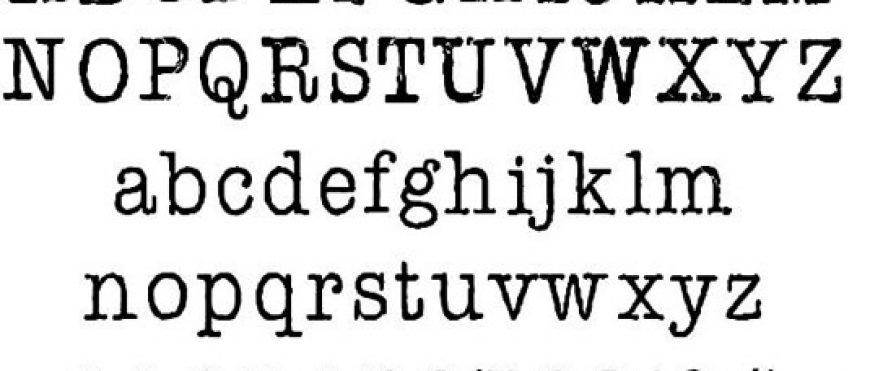
Создание атмосферы ретро: идеальный шрифт в стиле печатной машинки для ваших проектов
Шрифт в стиле печатной машинки приносит в дизайн ностальгическую атмосферу и ретро-шарм. Он идеально подходит для создания винтажных и креативных проектов, а также может быть использован для акцентов в современных дизайнах. В этой подборке вы найдете лучшие примеры таких шрифтов, а также полезные советы по их применению для достижения максимального эффекта.
При выборе шрифта в стиле печатной машинки обращайте внимание на его читаемость. Некоторые такие шрифты могут быть сложными для восприятия текста на экране.
Не бойтесь комбинировать шрифт в стиле машинки с современными элементами дизайна, чтобы создать интересный контраст между ретро и современностью.
Для улучшения визуального восприятия используйте шрифт в стиле печатной машинки в крупных заголовках, а не в длинных текстах, чтобы избежать перегрузки.
Если ваш проект связан с текстами, которые должны выглядеть как старые документы, выберите шрифт, имитирующий изношенные машинописные символы.
Добавляйте легкие текстурные эффекты, такие как «потертости» или «мельчайшие пятна», чтобы усилить эффект старинного документа.
Для создания ретро-атмосферы можно использовать шрифты с слегка «потрескавшимся» или «размытым» видом, что добавит тексту еще больше стиля и характера.
Не забывайте про контекст: шрифт в стиле печатной машинки лучше всего работает в проектах, где требуется подчеркнуть ностальгию или историческую атмосферу.
При использовании шрифта в стиле печатной машинки старайтесь придерживаться минималистичного дизайна, чтобы сам шрифт оставался в центре внимания.
Используйте цветовые акценты для выделения текста, но избегайте ярких оттенков, которые могут нарушить гармонию с ретро-стилем шрифта.
При работе с таким шрифтом важно помнить, что он не должен доминировать в дизайне, а лишь подчеркивать его уникальность и атмосферность.